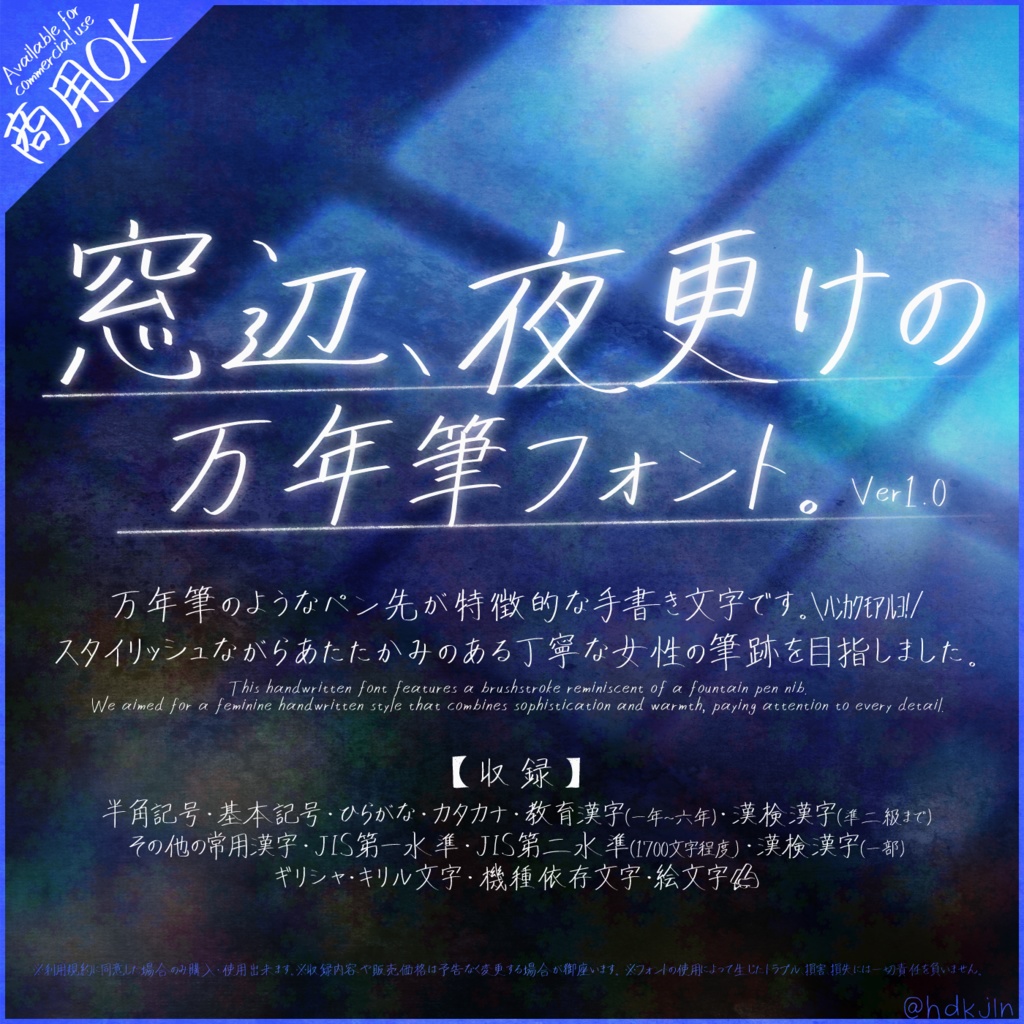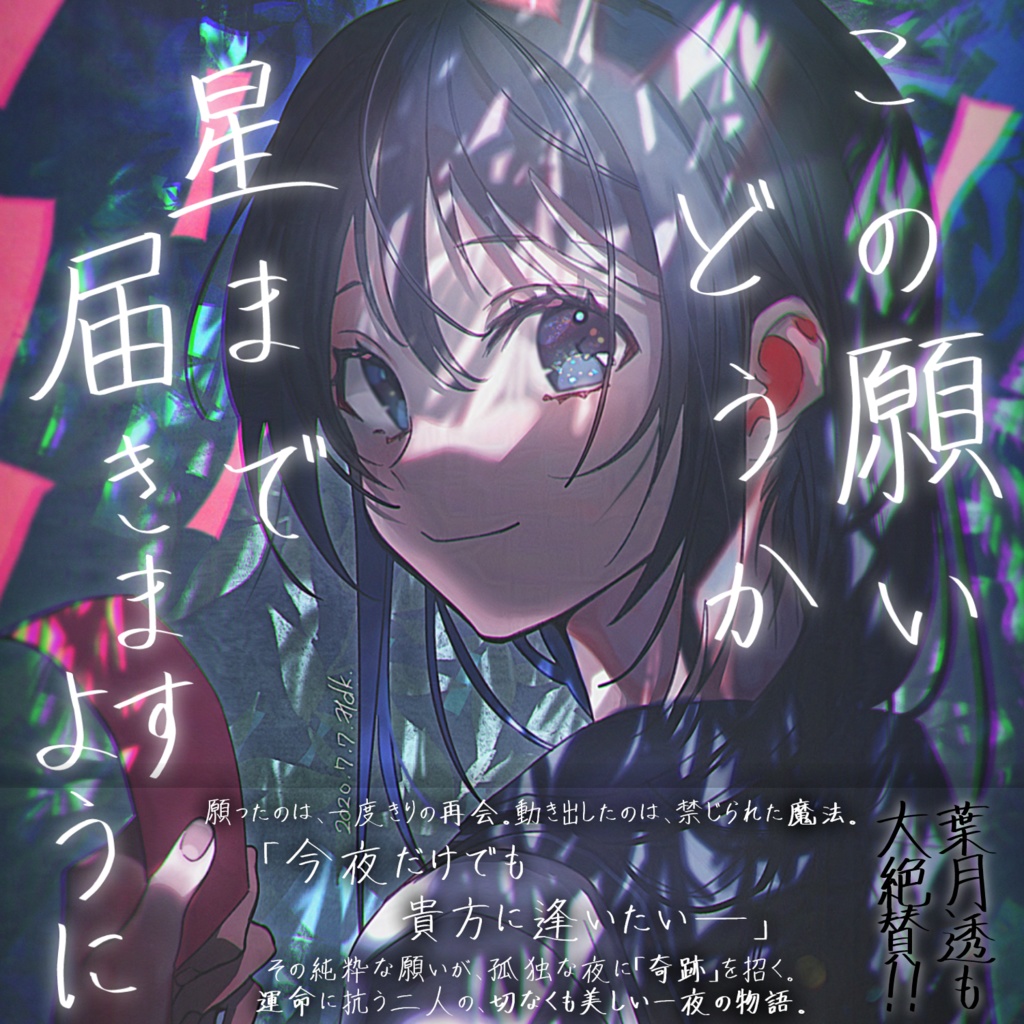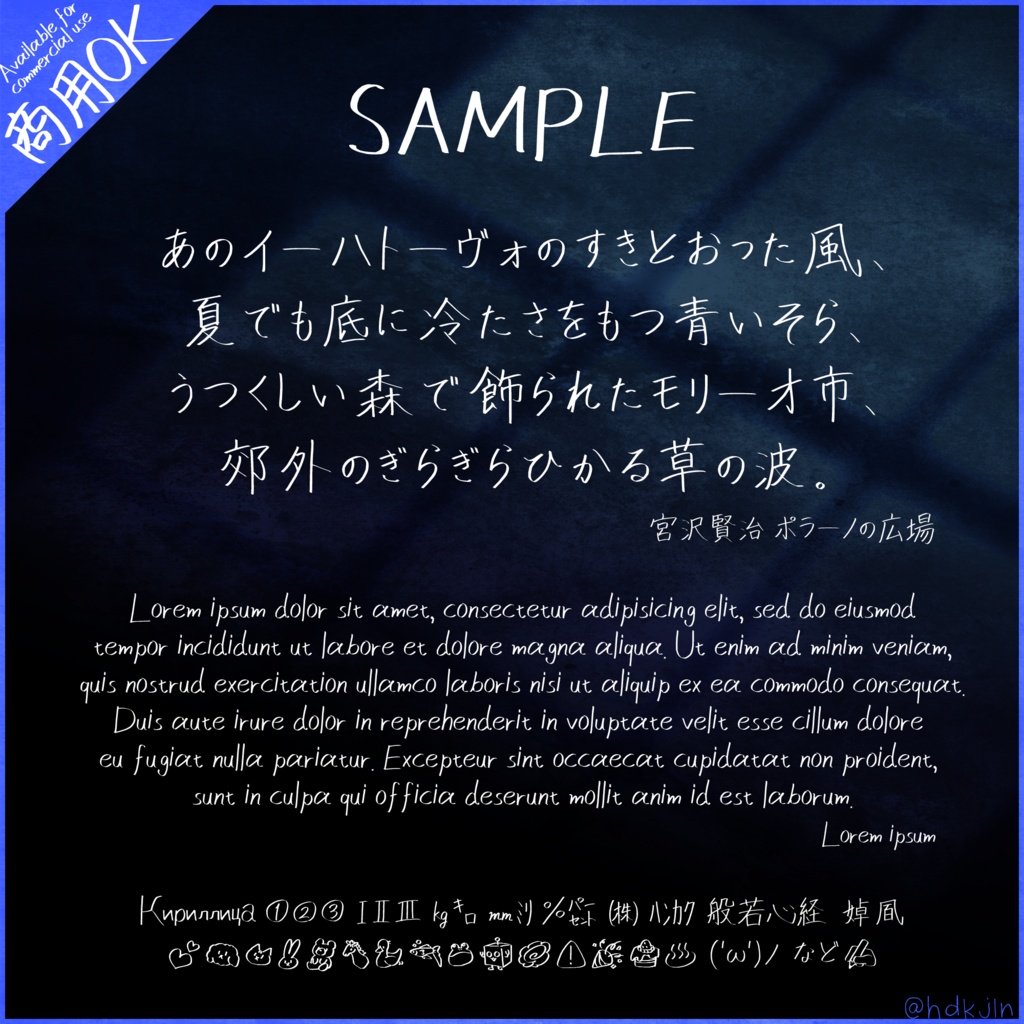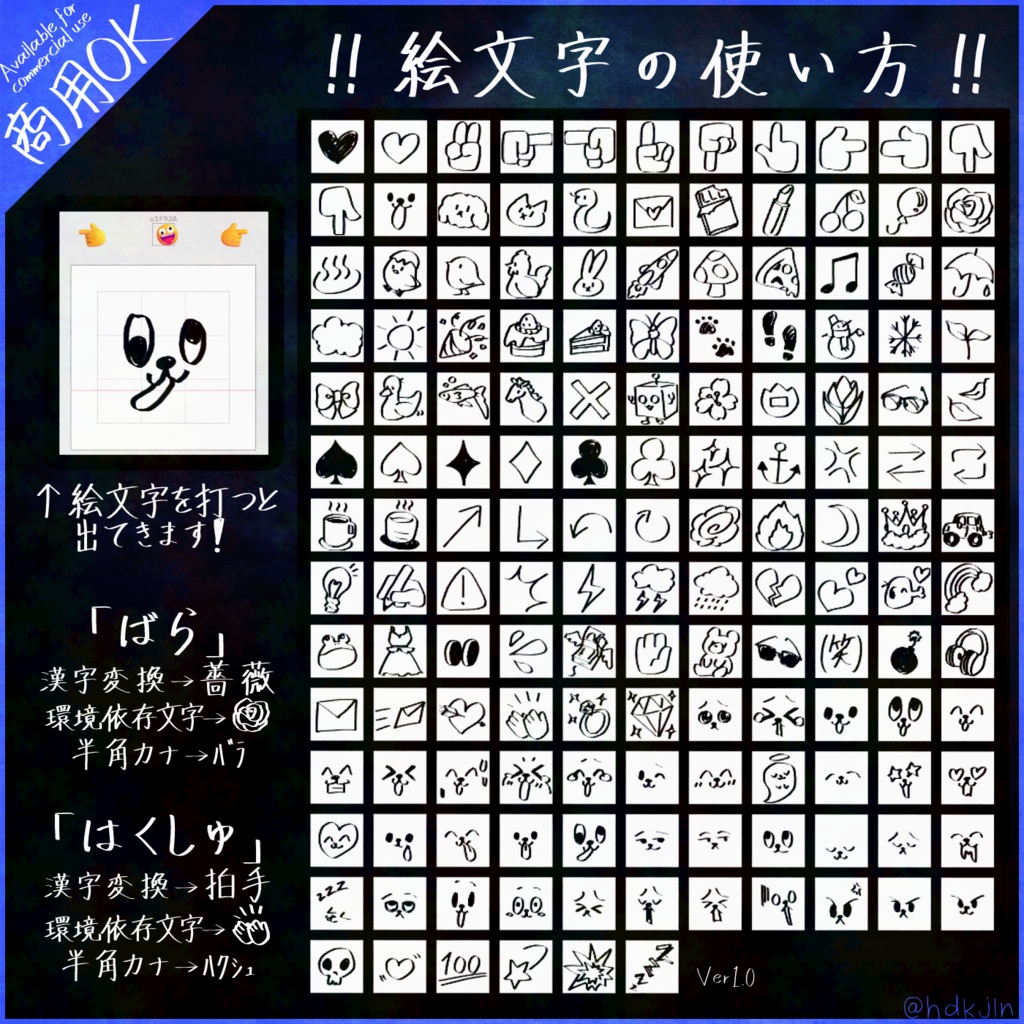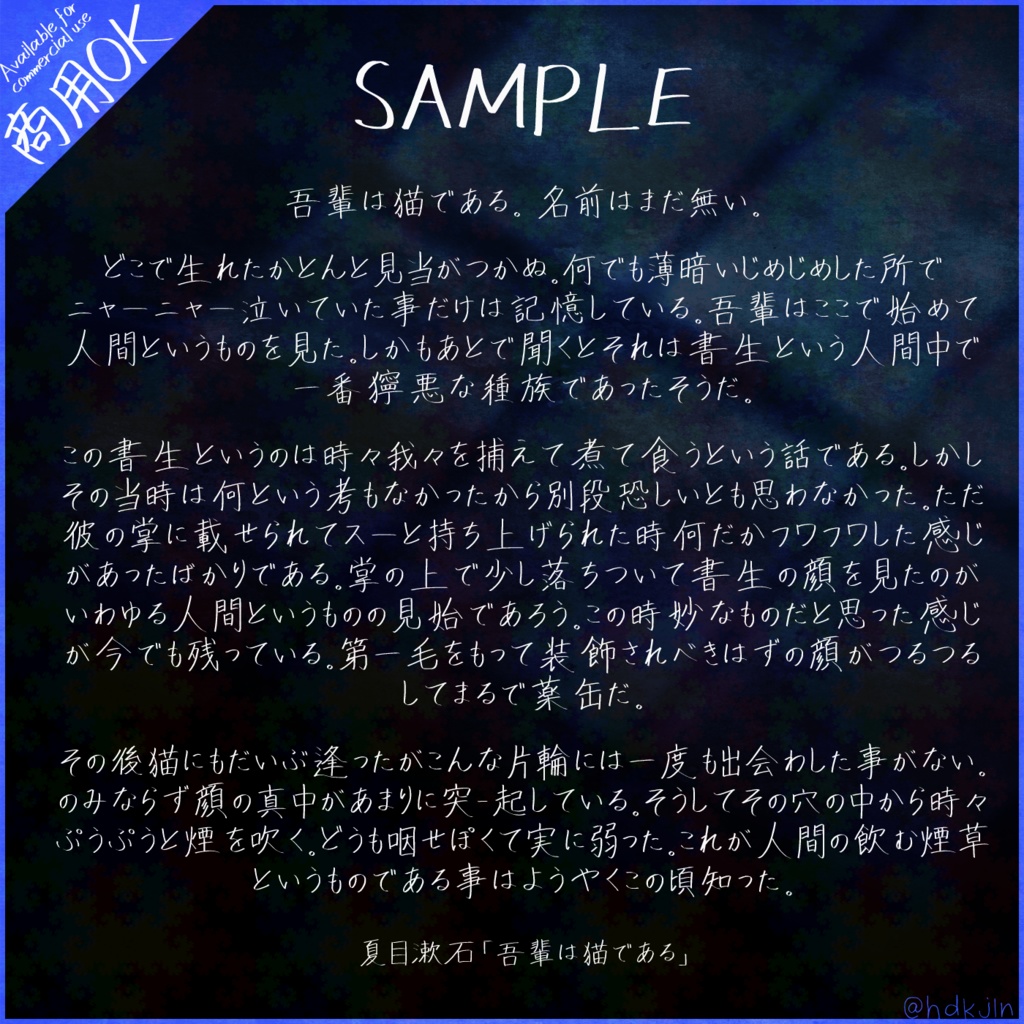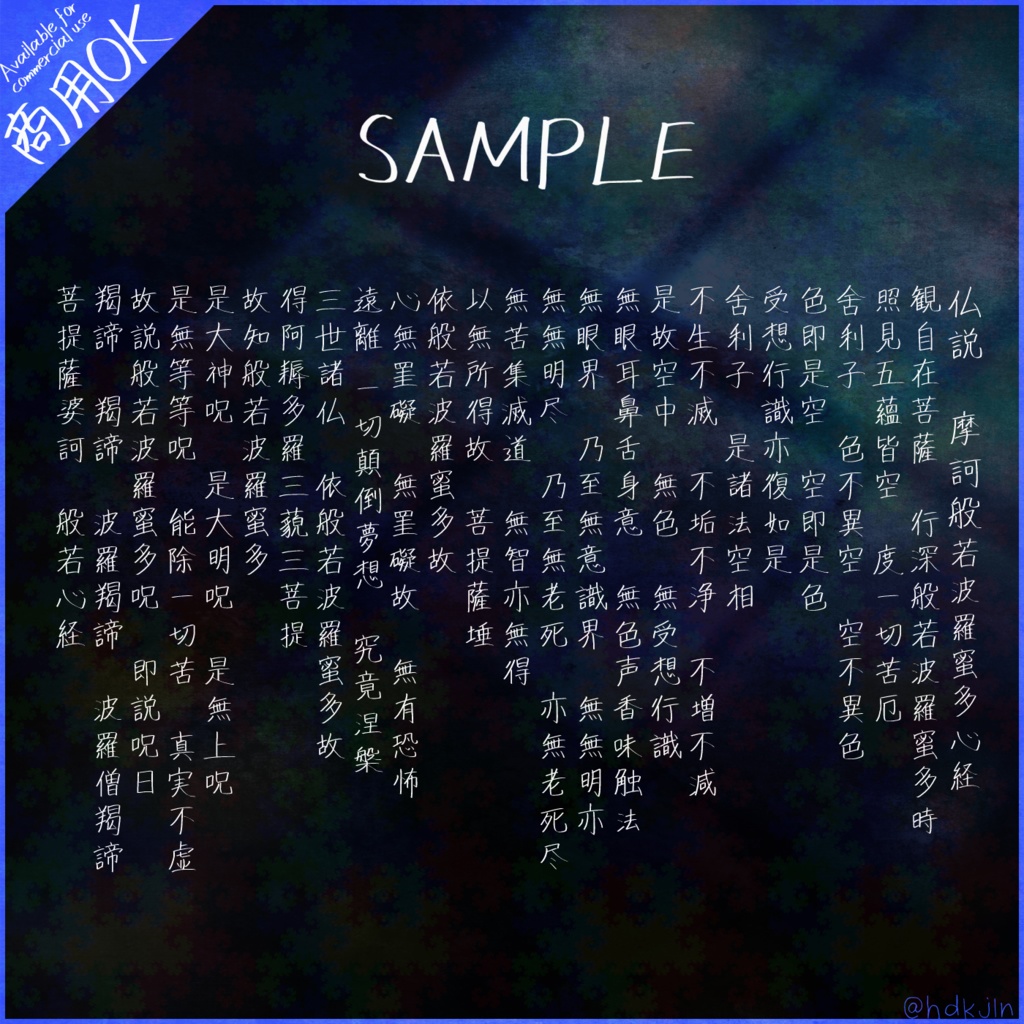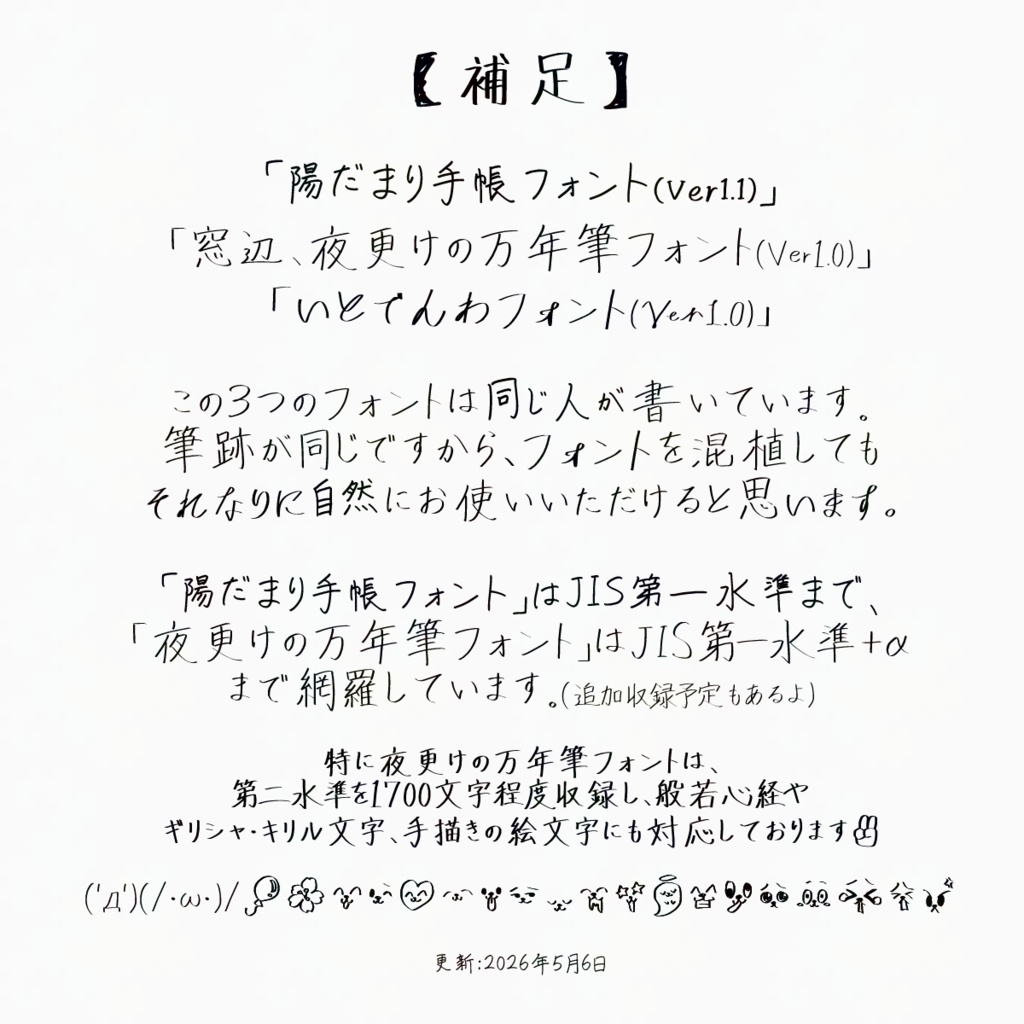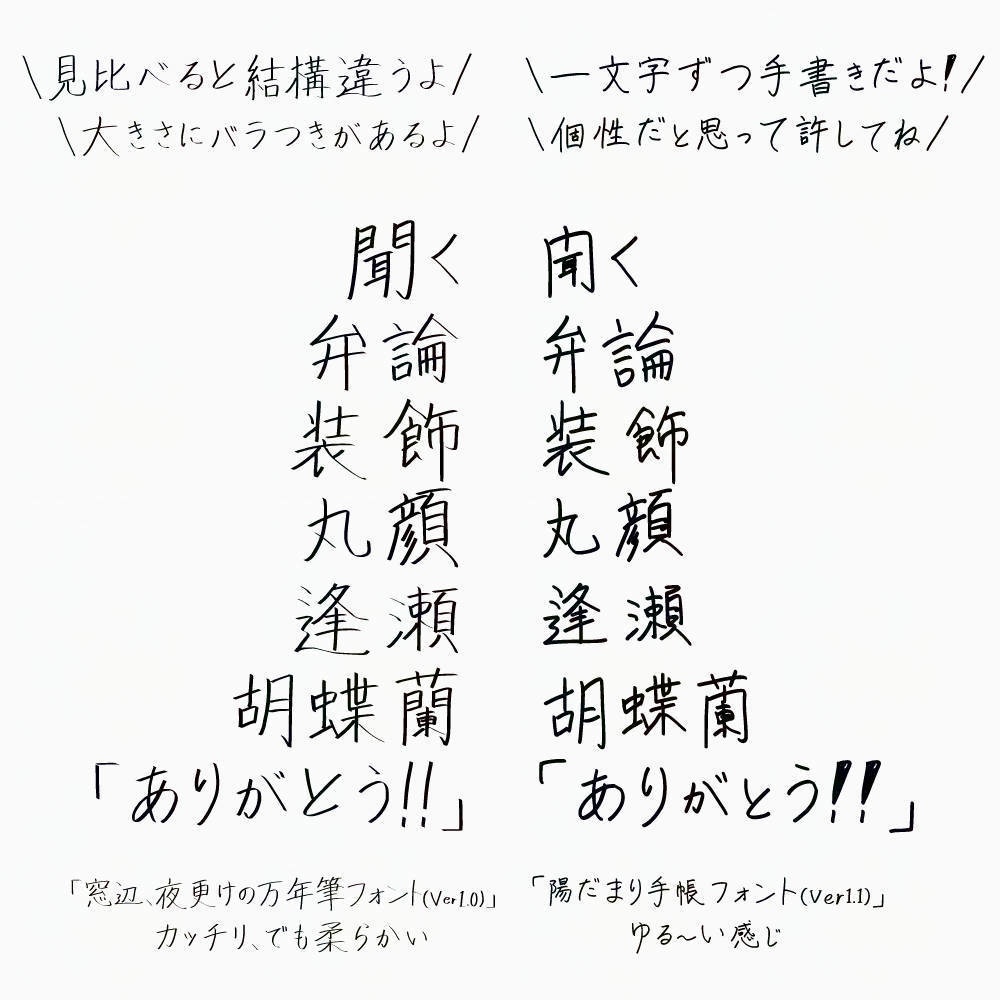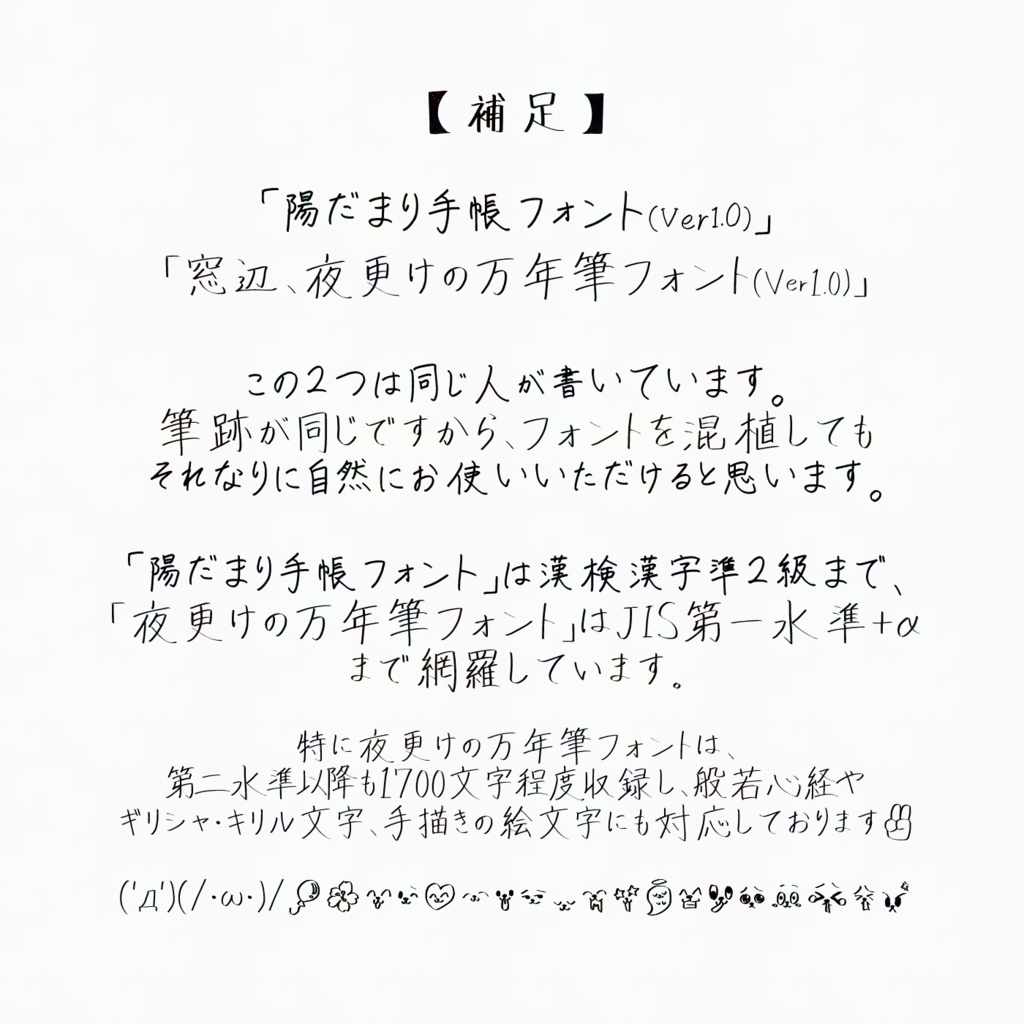
万年筆のようなペン先が特徴的な手書き文字です。\ハンカクモアルヨ!/ スタイリッシュながらあたたかみのある丁寧な女性の筆跡を目指しました。全て書き下ろしです。 This handwritten font features a brushstroke reminiscent of a fountain pen nib. We aimed for a feminine handwritten style that combines sophistication and warmth, paying attention to every detail. 【収録】 半角英数字 ・ 基本記号 ・ ひらがな ・ カタカナ ・ 教育漢字(一年~六年) ・ 漢検漢字(準二級まで)・その他の常用漢字 ・ JIS第一水準 ・ JIS第二水準(1700文字程度) ・ 漢検漢字(一部)・ギリシャ・キリル文字 ・ 機種依存文字 ・絵文字+α ※「婥」「凮」を収録しています。 ※ご要望がありましたら漢字を追加収録する可能性がございます。1文字だけでもお気軽にお問い合わせください! ※バージョンアップに伴う価格変更につきましては何卒ご了承ください。 ※本フォントの購入者・使用者は利用規約に同意したとみなします。 ご理解の程宜しくお願いいたします。 ーーーーーーーー ●フォント形式:OpenTypeフォント ●本フォントは、ばっと but (@buttaiwan) 様の「フォントを書こう! by 字嗨(buttaiwan.github.io)」を利用してフォントを制作しました。 ーーーーーーーー ■請求書について■ BOOTHの決済システムを利用しているため、当方から個別の領収書発行は原則行っておりません。購入時に発行されるメールや、マイページの購入履歴をもって代えさせていただきます。 法人間の取引等で、どうしても当方発行の請求書・領収書が必要な場合に限り、例外的にPDF形式での発行を承ります。ご希望の場合は、注文確定前にメールにてご連絡ください。 ーーーーーーーー ●文字を書いた人のパーソナリティ: 創作キャラなどの手書き文字(概念)として活用することもOKです!ご参考までに。 「陽だまり手帳フォント」「窓辺、夜更けの万年筆フォント」「糸電話フォント」→右利き/女性/Z世代/INTP 「春風手書きフォント」→右利き/女性/X世代/INFP 「小学一年生フォント」→左手で指書き